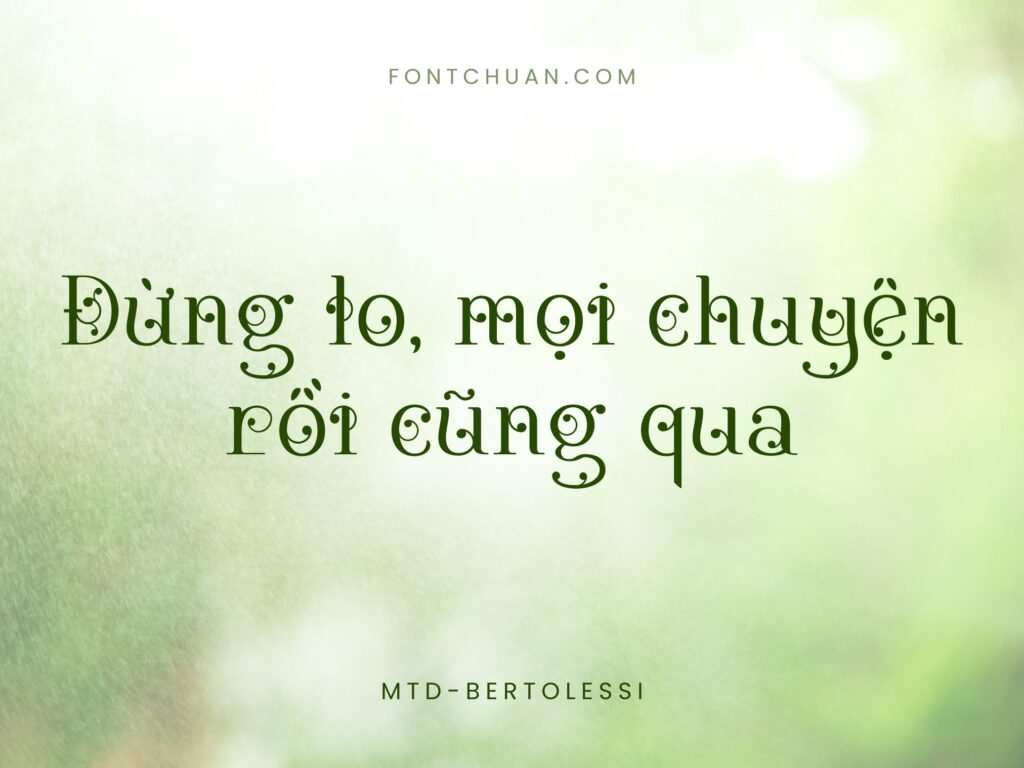
Font MTD Bertolessi Việt Hóa
Tác giả Font: Greater Albion Typefounders
Bertolessi là một font chữ cổ điển được thiết kế bởi Greater Albion Typefounders, mang phong cách hoài cổ kết hợp với đường nét sang trọng. Font này nổi bật với các ký tự có đường viền tinh tế, mang đến vẻ đẹp nghệ thuật và đậm chất retro. Để giúp font này trở nên dễ dàng sử dụng hơn tại Việt Nam, Mộc Hạ đã Việt hóa Bertolessi, giúp hỗ trợ đầy đủ tiếng Việt cùng hơn 200 ngôn ngữ khác. Phiên bản Bertolessi Việt hóa đã được thành viên Font Chuẩn sưu tầm và đăng tải nhằm mang đến nhiều sự lựa chọn hơn cho các nhà thiết kế.
Về đặc điểm thiết kế, Bertolessi sở hữu những ký tự thanh thoát với độ uốn lượn tinh tế, phù hợp với phong cách hoài cổ nhưng vẫn giữ được tính hiện đại. Font này rất phù hợp cho các thiết kế thương hiệu, bao bì sản phẩm, typography nghệ thuật và bìa sách. Ngoài ra, Bertolessi cũng là một lựa chọn lý tưởng cho các ngành nghề như quảng cáo, bất động sản và giáo dục, giúp mang lại phong cách sang trọng và đẳng cấp. Font này cũng rất thích hợp để sử dụng trong các sự kiện như Valentine, Sinh nhật và các lễ hội.